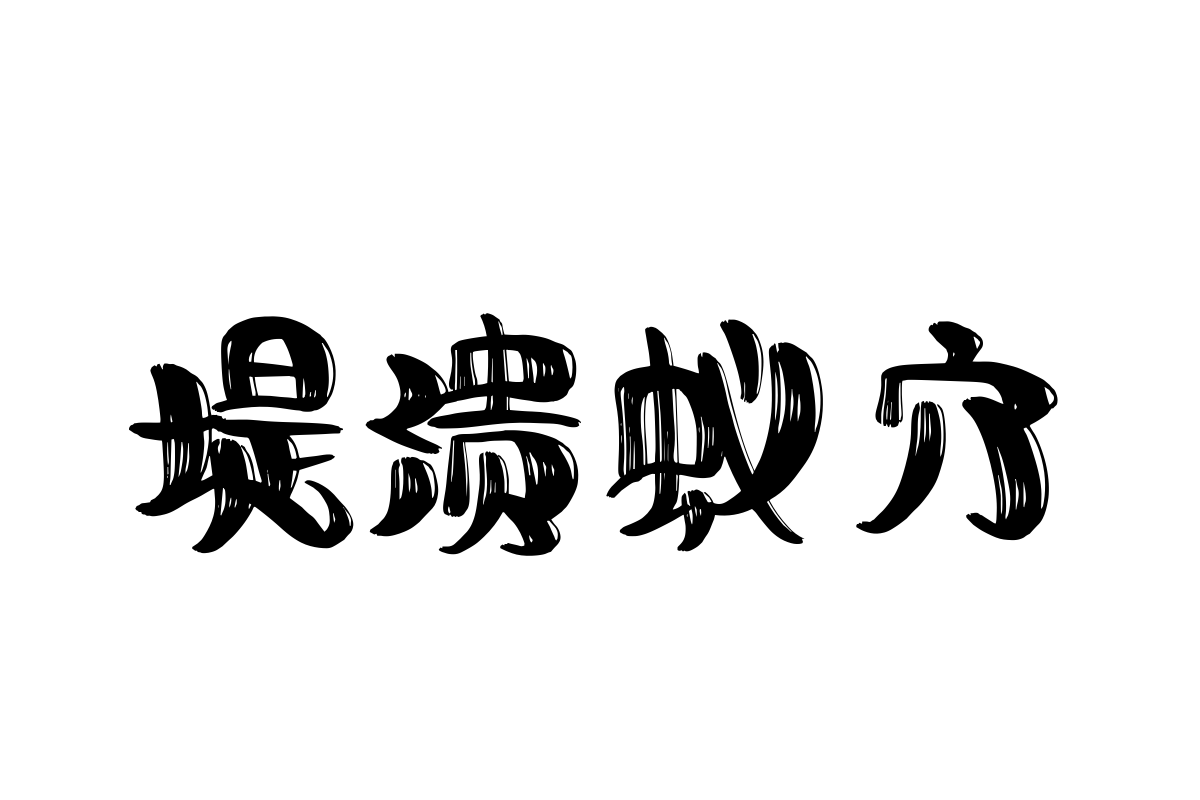
汉仪喵魂梦境 W 是一款具有现代感的字体,它采用了一种独特的设计风格,将传统的汉字与现代元素相结合。这款字体的特点在于其笔画流畅、结构紧凑,给人一种简洁而又有力量的感觉。
在设计上,汉仪喵魂梦境 W 采用了一种类似于漫画风格的线条,使得整个字体看起来更加生动有趣。同时,这款字体还融入了一些现代的设计元素,如渐变、立体等,使得整体效果更加独特。
总的来说,汉仪喵魂梦境 W 是一款非常有特色的字体,适合用于需要强调个性和创意的场合。